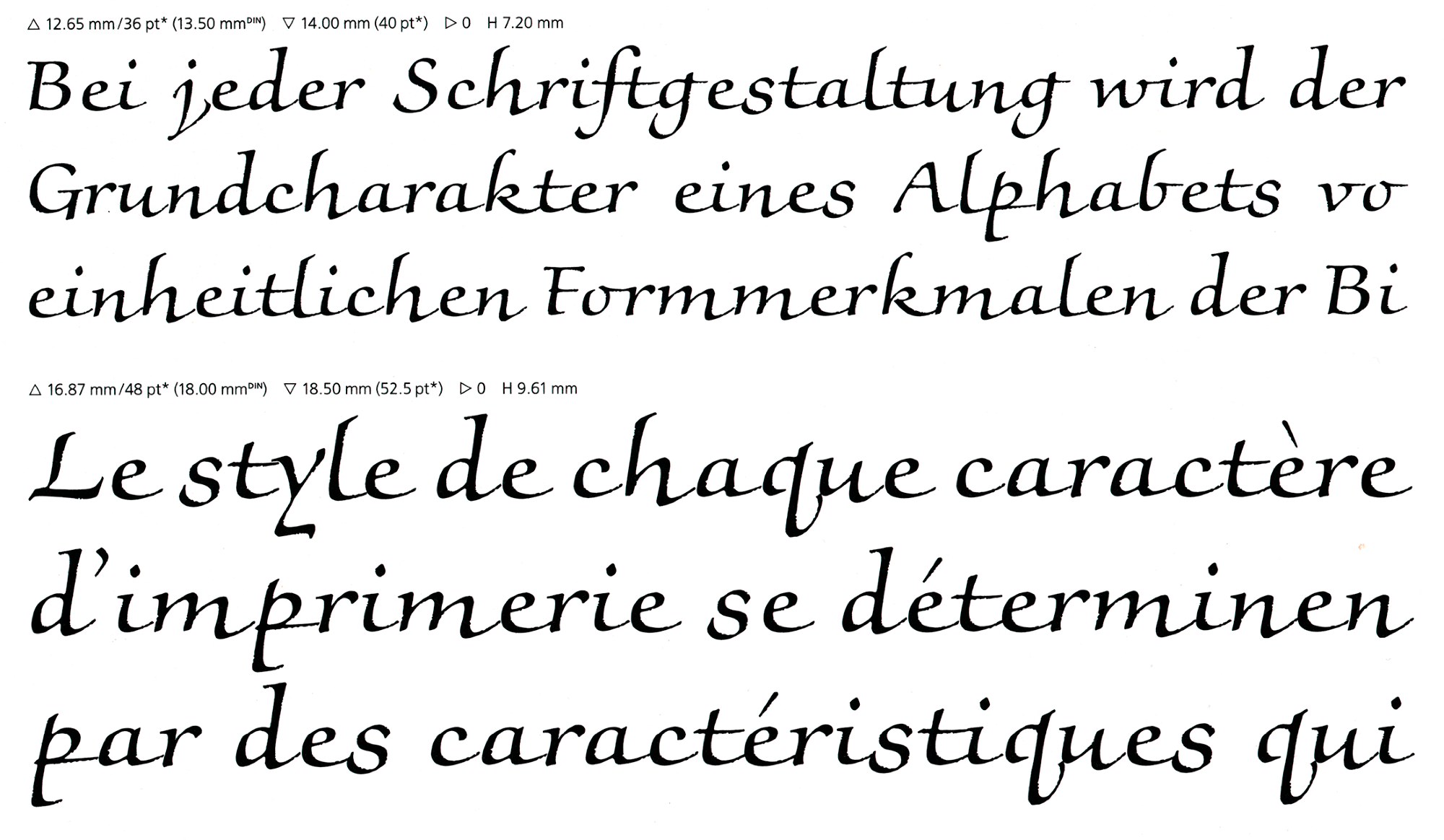
Die Noris Script ist eine Schreibschrift von Hermann Zapf mit kalligrafischem Duktus und rauer Umrisslinie. Die Schrift erschien in den 1970er-Jahren als Fotosatzschrift bei Linotype und ist als digitale Version mit erweiterter lateinischer Belegung als Noris Script Pro erhältlich.